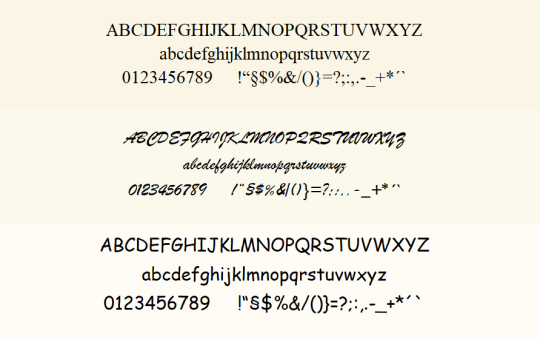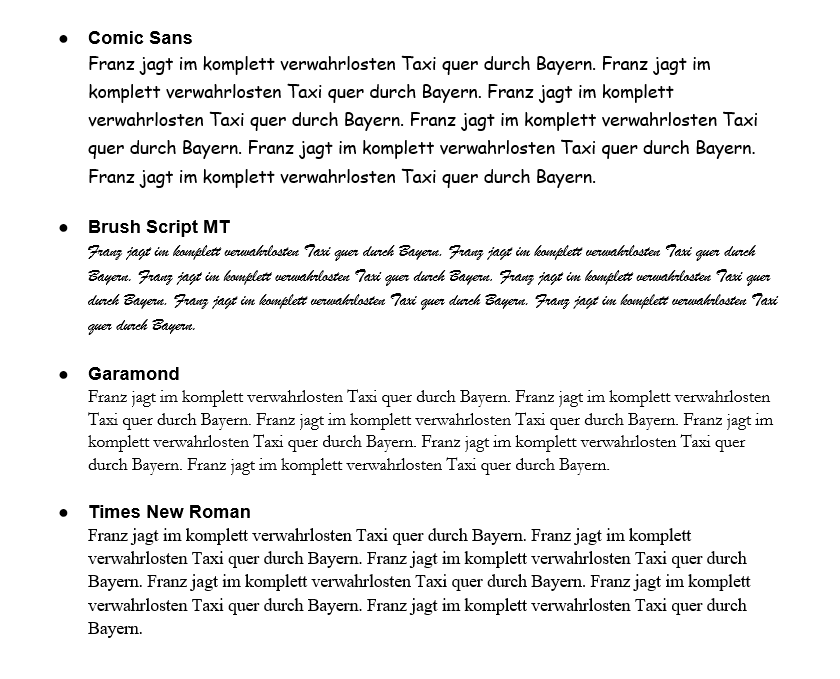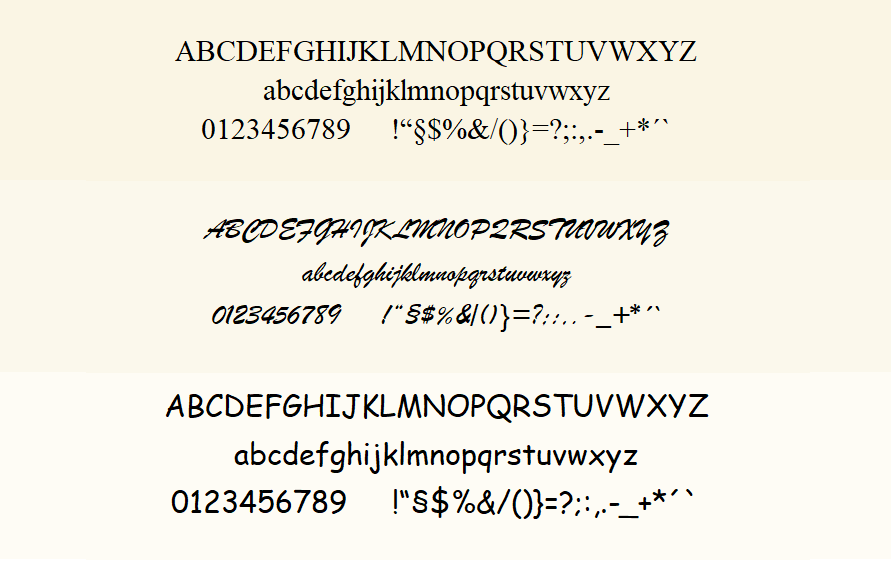
In der Welt der Druckprodukte ist auch die Auswahl der richtigen Schriftart entscheidend, um Ihren Dokumenten das gewisse Etwas zu verleihen.
Microsoft Word bietet eine beeindruckende Auswahl an Schriftarten, die von klassisch elegant bis hin zu modern und verspielt reichen. Wenn Sie nach Inspiration für Ihre Schriftarten in Word suchen, sind Sie hier genau richtig.
Warum ist die Auswahl der richtigen Schriftart wichtig?
Sich dem Einfluss von Schriften zu entziehen, klappt ungefähr genauso gut, wie in der heutigen Zeit ohne Handy unterwegs zu sein … Schriften verfolgen uns auf Schritt und Tritt.
Aus diesem Grund kann die Schriftart, die Sie wählen, maßgeblich dazu beitragen, wie Ihre Botschaft wahrgenommen wird:
- Lesbarkeit und Verständlichkeit: Eine gut gewählte Schriftart verbessert die Lesbarkeit eines Textes und trägt dazu bei, dass die Botschaft klar und leicht verständlich ist.
- Ästhetik und Wirkung: Die Schriftart trägt maßgeblich zur Ästhetik eines Dokuments bei und beeinflusst die Wirkung auf den Leser. Sie kann die Stimmung und den Ton des Textes vermitteln - von formell und professionell bis hin zu locker und kreativ.
- Markenidentität: Im geschäftlichen Kontext trägt die Wahl einer bestimmten Schriftart zur Festlegung der Markenidentität bei. Eine konsistente Verwendung der Schriftart in Marketingmaterialien und anderen Unterlagen stärkt das Markenimage und die Wiedererkennung einer Marke.
- Anpassung an den Einsatzzweck: Ein besonderer Inhalt eines Textes erfordert eine passende Schriftart. Zum Beispiel sind für formelle Dokumente oder berufliche Präsentationen eher traditionelle Schriftarten geeignet, während für kreative Projekte oder informelle Mitteilungen verspielte oder moderne Schriftarten bevorzugt werden können.
- Kulturelle Bedeutung: Bestimmte Schriftarten können kulturelle Assoziationen hervorrufen oder historische Bedeutung haben. Zum Beispiel wird die Schriftart "Gothic" oft mit mittelalterlicher Ästhetik in Verbindung gebracht, während z.B. "MS Mincho" eine asiatisch anmutende Schriftart ist.
Die Auswahl der richtigen Schriftart hat einen erheblichen Einfluss darauf, wie ein Text wahrgenommen und wie effektiv er kommuniziert wird. Es ist daher wichtig, sorgfältig zu wählen sowie immer die Zielgruppe im Blick zu haben.
Klassisch: Zeitlose Schriftarten
Klassische Schriftarten wie
- Times New Roman,
- Arial und
- Calibri
sind zeitlose Optionen für Ihren Text.
Sie werden häufig in formellen Dokumenten wie wissenschaftlichen Arbeiten, Berichten, Geschäftsbriefen und anderen professionellen Unterlagen verwendet. Ihre klassische Erscheinung verleiht den Texten eine gewisse Eleganz und Seriosität, während ihre gute Lesbarkeit sowohl im gedruckten als auch im digitalen Format geschätzt wird.
Moderne Eleganz: Schriftarten mit Flair
Für einen modernen und stilvollen Look bieten sich Schriftarten wie
- Helvetica,
- Garamond und
- Futura an.
Diese Schriftarten zeichnen sich durch ihre klaren, geraden Linien, gleichmäßige Proportionen und eine ausgezeichnete Lesbarkeit aus. Diese Eigenschaften machen sie zu vielseitigen Schriftarten, die sich für eine breite Palette von Anwendungen eignen, von Texten jeglicher Art bis hin zu Websites, Beschilderungen, Logos und mehr.
Ihr minimalistisches Design und ihre Neutralität haben die oben genannten Schriftarten zu einer beliebten Wahl für Designer gemacht, die nach einer Schriftart suchen, die unauffällig und dennoch präsent ist. Sie werden oft für ihre zeitlose Ästhetik und ihre Fähigkeit gelobt, sich nahtlos in verschiedene Designstile einzufügen.
Verspielte Kreativität: Schriftarten mit Charakter
Wenn Sie Ihren Dokumenten eine persönliche Note verleihen möchten, sollten Sie Schriftarten wie z.B.
- Comic Sans,
- Brush Script MT oder
- Lucinda Handwriting
in Betracht ziehen.
Die Wahl der richtigen Schriftart für Ihr Druckprodukt hängt von verschiedenen Faktoren ab, darunter die Art des Dokuments, die Zielgruppe und der gewünschte visuelle Stil.
Es ist daher wichtig, eine Schriftart zu wählen, die die Botschaft effektiv vermittelt und gleichzeitig eine angemessene Lesbarkeit und Ästhetik bietet.
Schöne Schriftarten für Hochzeitspapeterie
Bei der Auswahl von schönen Schriftarten für Hochzeitseinladungen, Dankeskarten, etc. ist es wichtig, Schriftarten zu wählen, die sowohl elegant als auch gut lesbar sind. Hier sind einige beliebte und schöne Schriftarten (nicht alle in Word verfügbar), die oft für Hochzeiten verwendet werden:
Klassische Serifen-Schriftarten:
- "Cormorant Garamond"
- "Playfair Display"
- "Cinzel"
Elegante Sans-Serif-Schriftarten:
- "Montserrat"
Beispiel-Pangramme mit den folgenden Schriftfonts:
In den oben dargestellten Pangrammen ist gut zu erkennen, wie unterschiedlich eine Textpassage, bei verschiedenen Schriftarten wirken kann.